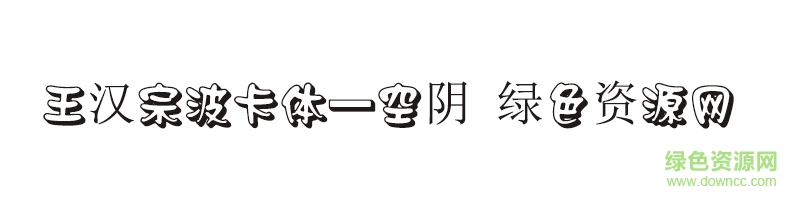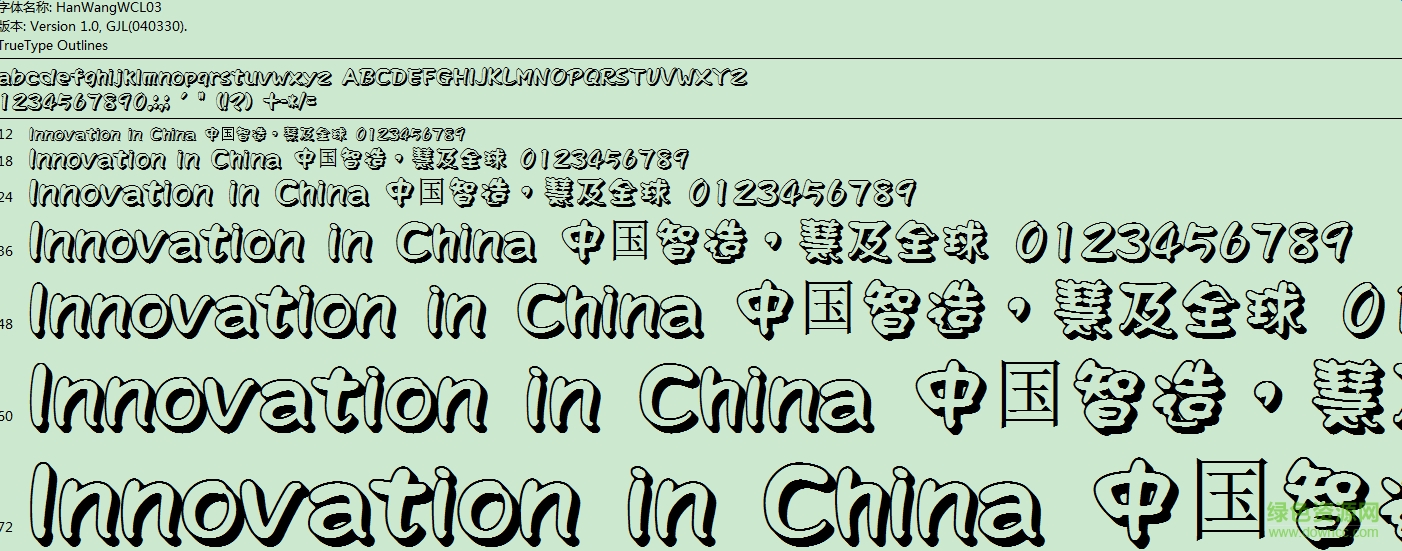
王漢宗波卡體一空陰字體是一款王漢宗字體,可以用于廣告設(shè)計、海報設(shè)計等方面,字形非常有趣,有需要的朋友快來綠色資源網(wǎng)免費下載哦!
空陰的筆型厚實有力,字構(gòu)平穩(wěn)扎實,具有濃厚的書法氣息,此款為空陰空心效果,適合包裝設(shè)計、海報設(shè)計、畫冊設(shè)計等廣告設(shè)計場合使用。